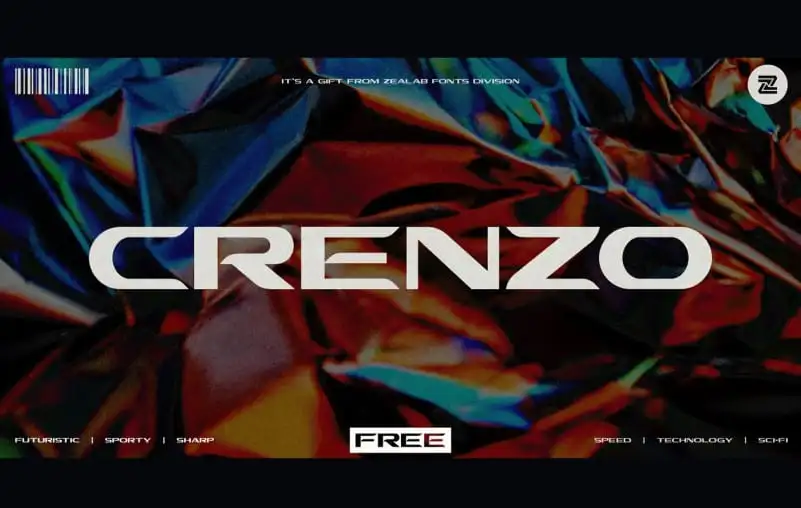
Crenzo Display Font
A Crenzo Display Font é perfeita para seus próximos projetos digitais. Esta nova fonte sans-serif livre foi criada pela Zea Fonts e está repleta de elementos futuristas modernos, incluindo caracteres maiúsculos e minúsculos, números e pontuação. Perfeitamente adaptável a áreas como logotipos, títulos, embalagens, design para web e aplicativos, entre outras diversas aplicações. Seus traços sóbrios e elegantes fazem dela uma opção ideal para o espaço tecnológico e de jogos, criando um visual arrojado que pode se destacar em qualquer projeto digital. Como parte do catálogo da Zea Fonts, a Crenzo é uma fonte ideal para designers buscando elementos distintivos para seus projetos digitais.